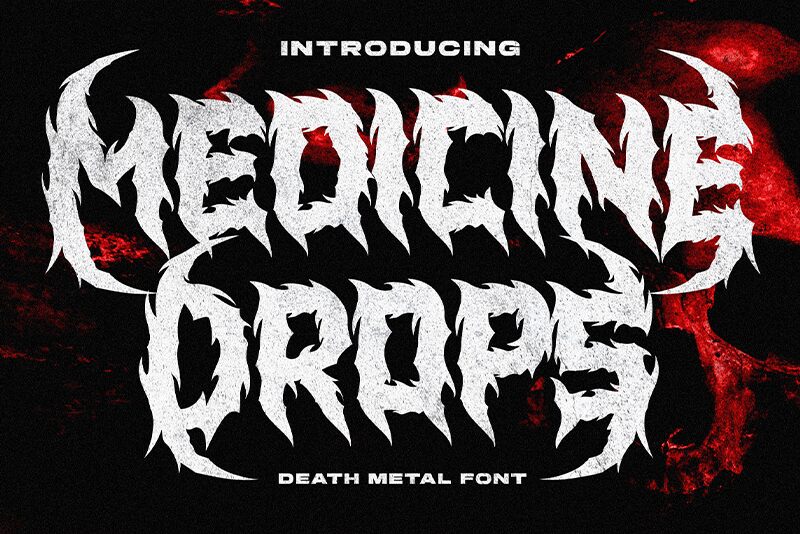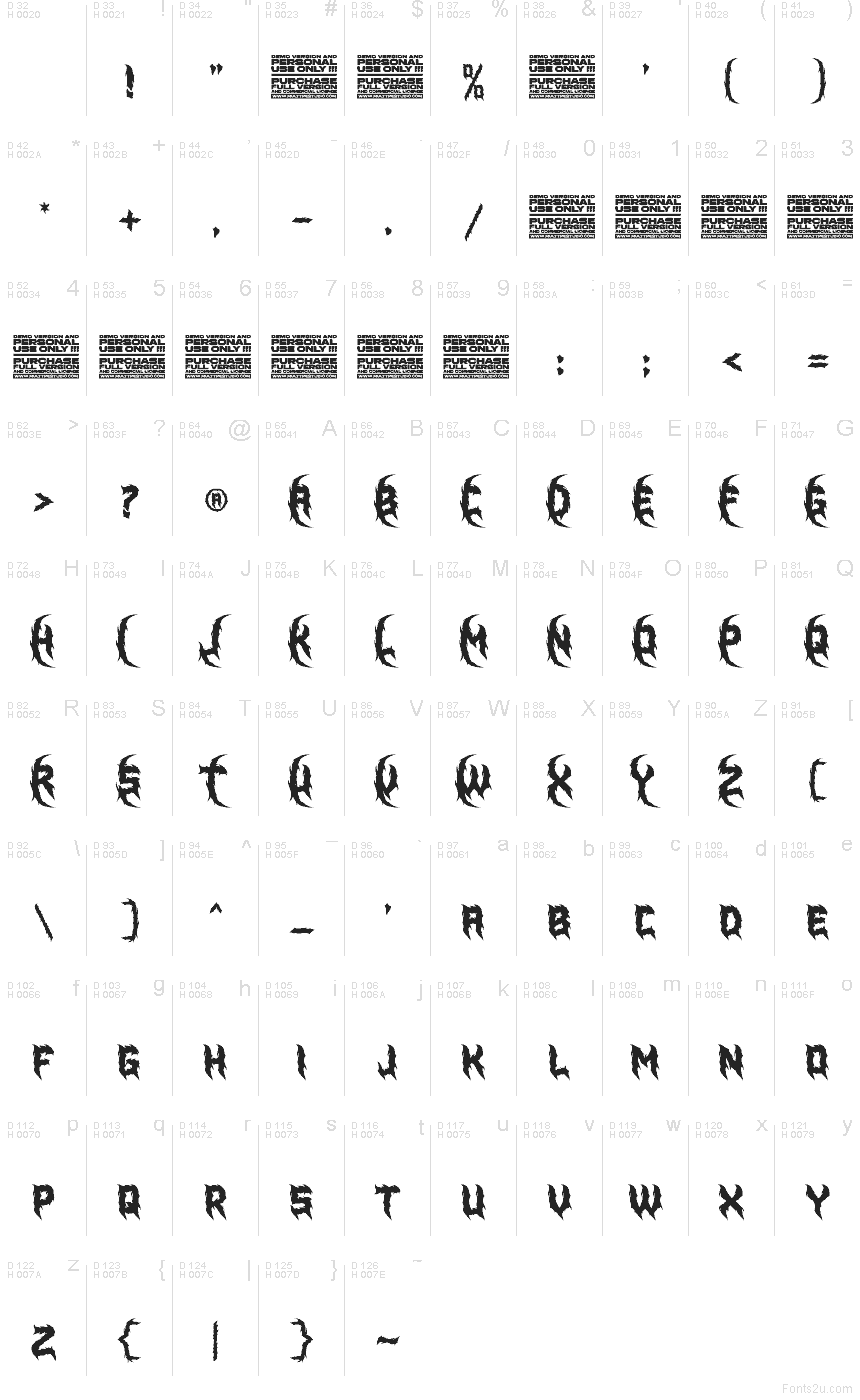
Medicine Drops
Medicine Drops by Medicine Dropsは、鋭く引き裂かれたようなエッジと炎のような切り込みが特徴の無料のゴシック系ディスプレイフォントです。各文字に歪んだ不規則なアウトラインを与えています。なめらかさよりも彫り込まれたようなダメージ感があり、尖った先端と荒々しい内部の割れ目が、攻撃的で手書きのような質感を生み出しています。
Medicine Dropsは、ホラー映画のポスター、メタルバンドのアルバムカバー、ゲームのタイトル、お化け屋敷のチラシ、不気味なイベントのグラフィックなどに最適です。そのギザギザした形状は、装飾を加えなくてもダークで傷ついた雰囲気を醸し出します。また、ハロウィンのパッケージデザイン、グランジ風のロゴ、ソーシャルメディア用のドラマチックなアートワークなど、ひび割れた、不安感をかき立てるような手作りの質感を求めるデザインにもぴったりです。